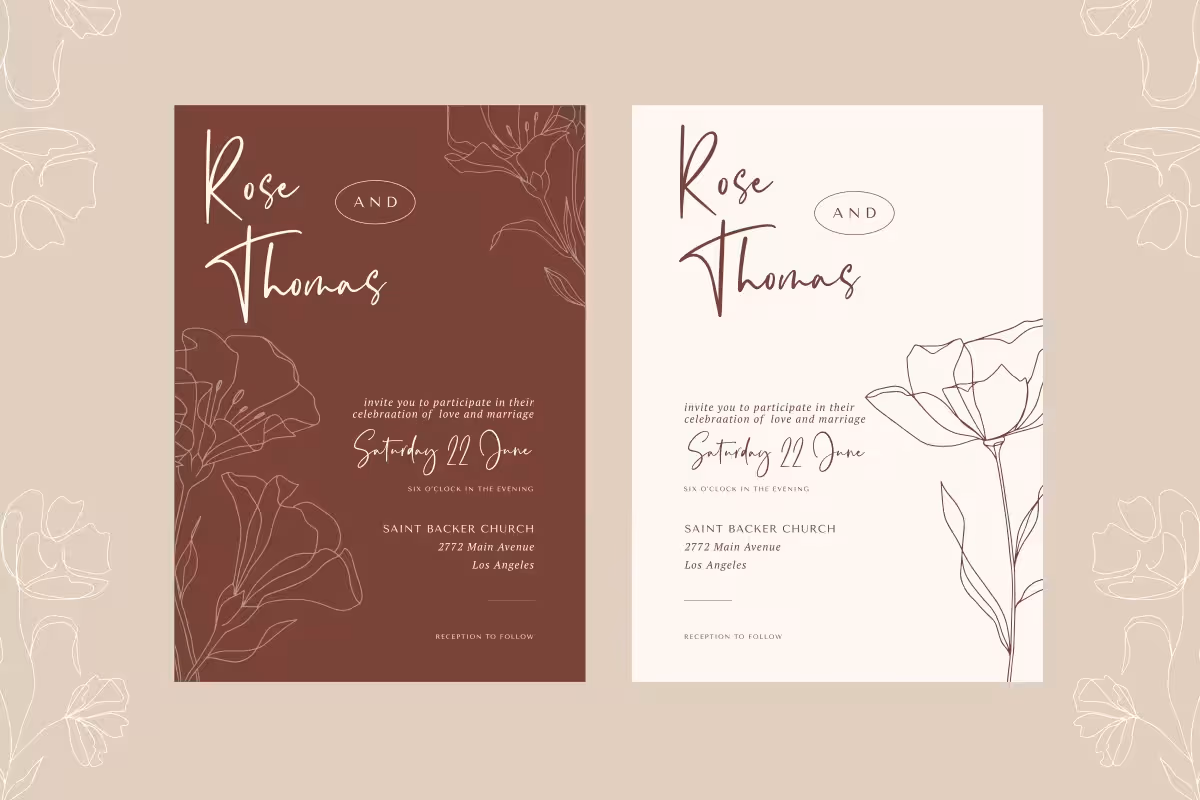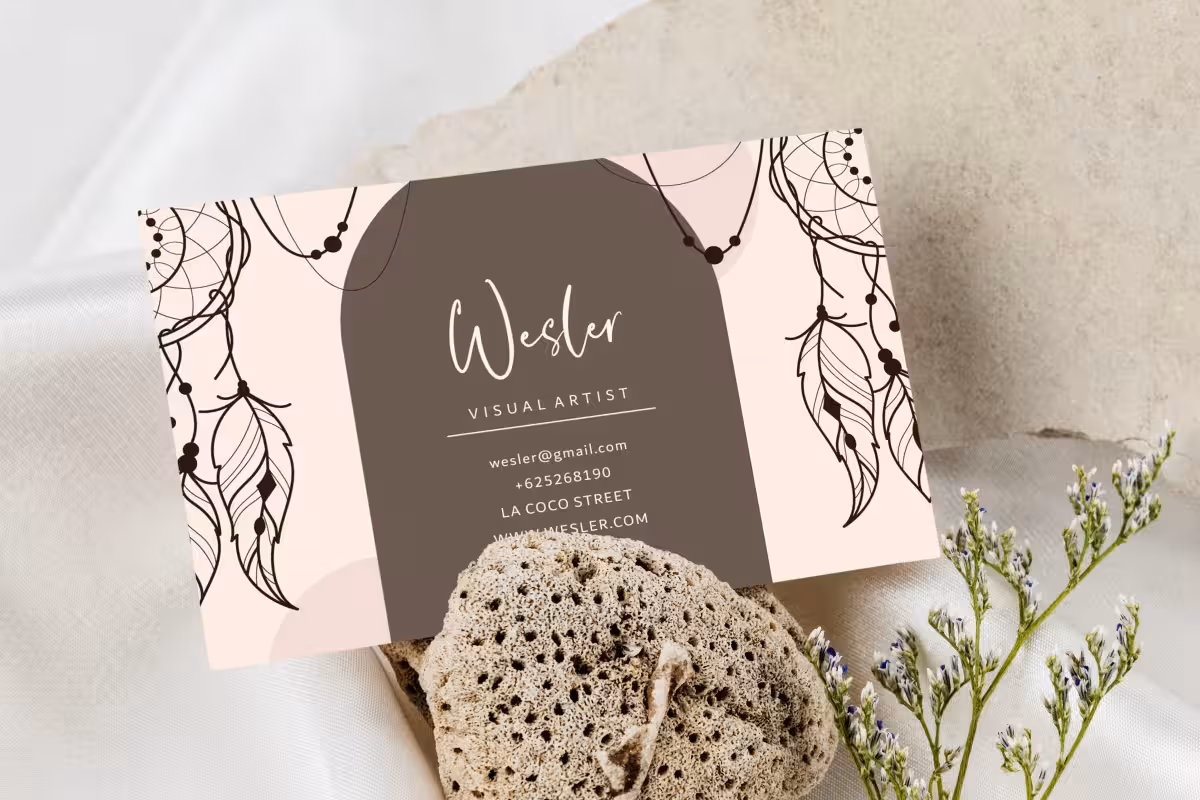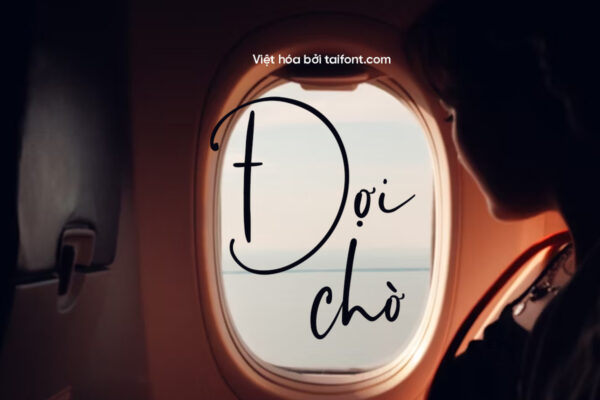
Giới thiệu về Font TF Cinemathic Visualation Việt hóa
TF Cinemathic Visualation Việt hóa là một font chữ viết tay (script font) nổi bật với vẻ đẹp tinh tế, bay bổng và đầy cá tính, gợi nhớ đến những nét chữ ký của người nổi tiếng hay những thước phim nghệ thuật. Font này mang đến cảm giác như một bức thư pháp được viết tay một cách mềm mại và uyển chuyển, toát lên sự sang trọng, lãng mạn và đẳng cấp, lý tưởng để tạo điểm nhấn độc đáo và thu hút mọi ánh nhìn.
Với sự duyên dáng trong từng đường nét và tính thẩm mỹ cao, Cinemathic Visualation là lựa chọn hoàn hảo cho các thiết kế muốn truyền tải sự tinh tế, nghệ thuật và sự cá nhân hóa:
- Chữ ký và branding cá nhân: Hoàn hảo để tạo chữ ký điện tử, logo cá nhân, hoặc các yếu tố nhận diện thương hiệu muốn thể hiện sự độc đáo và phong cách riêng, đặc biệt trong lĩnh vực nghệ thuật, sáng tạo.
- Thiết kế thiệp: Lý tưởng để viết lời chúc, lời mời, hoặc các thông điệp cá nhân trên thiệp sinh nhật, thiệp kỷ niệm, thiệp cưới. Nét chữ viết tay thanh lịch của font sẽ làm cho mỗi tấm thiệp trở nên độc đáo, ấm áp và đầy ý nghĩa.
- Thiết kế thời trang: Phù hợp cho các thương hiệu thời trang cao cấp muốn truyền tải sự tinh tế, độc đáo và một chút phong cách thủ công. Font có thể dùng cho logo, nhãn mác sản phẩm, in ấn trên trang phục hoặc các chiến dịch quảng bá bộ sưu tập.
- Banner decor và trang trí: Tuyệt vời để sử dụng trên các banner trang trí, poster hoặc các ấn phẩm muốn tạo không khí lãng mạn, nghệ thuật và sang trọng cho sự kiện, cửa hàng hoặc không gian sống.
Với TF Cinemathic Visualation Việt hóa, bạn có thể dễ dàng thổi hồn nghệ thuật, sự tinh tế và vẻ đẹp lãng mạn vào các thiết kế, tạo ra những sản phẩm không chỉ đẹp mắt mà còn đầy cảm xúc và sức hút đặc biệt.